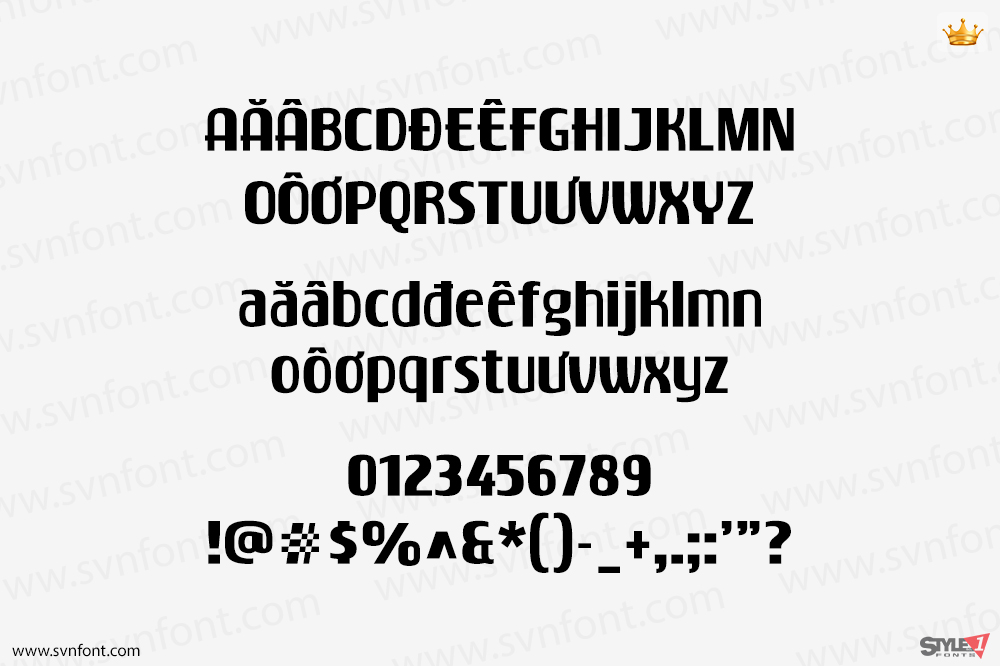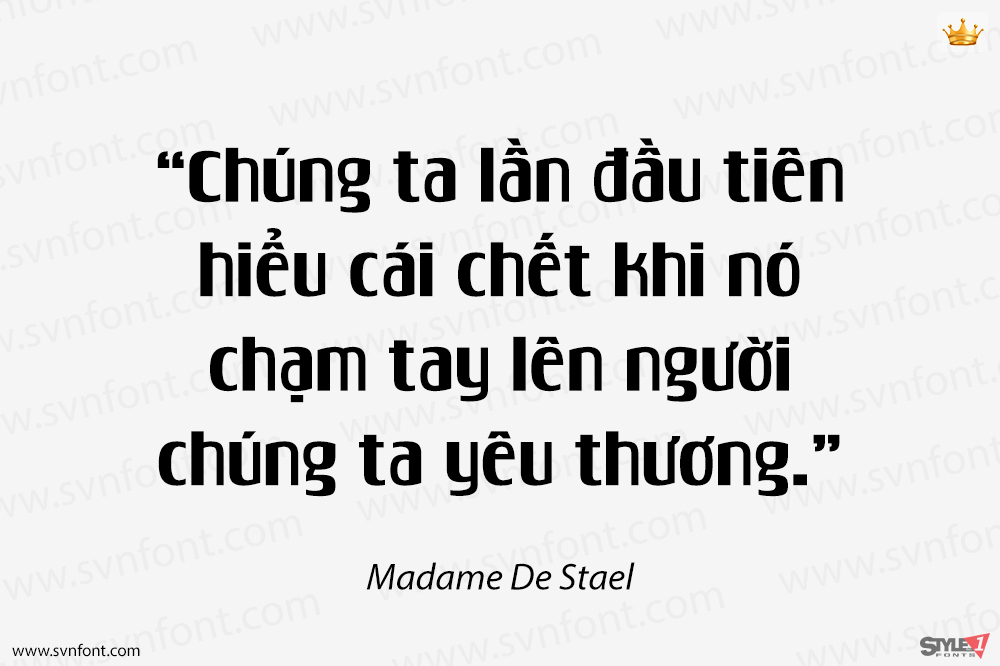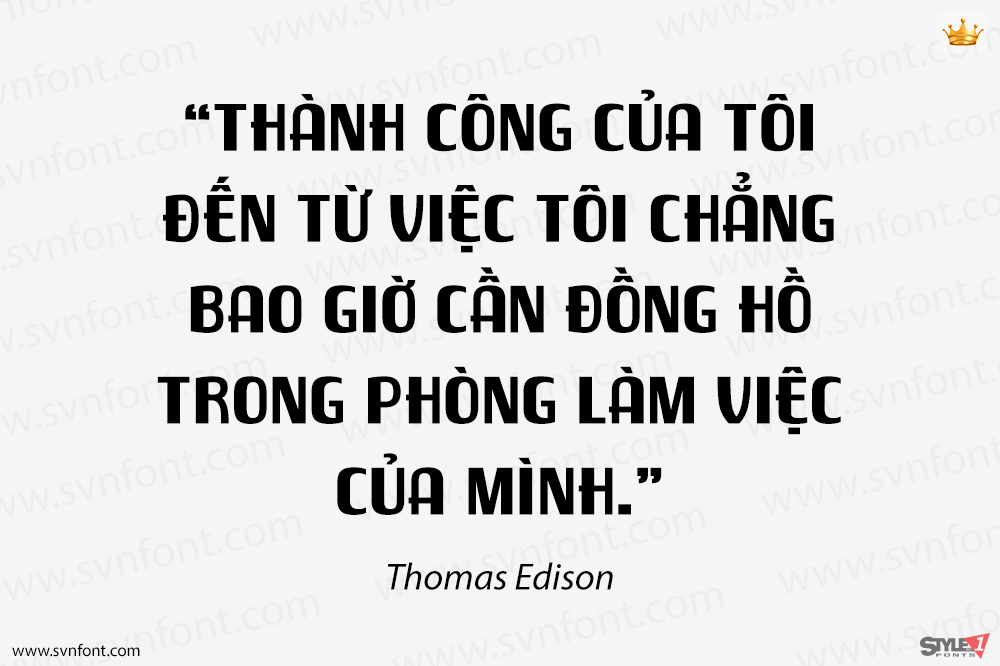
“CUMBANCHERA”, lấy cảm hứng từ nghệ thuật bìa album nhạc Latinh cổ điển. Cumbanchera gợi nhớ đến chủ đề âm nhạc mang tính biểu tượng, cổ điển và được công nhận «El Cumbanchero» do Rafael Hernández Marín «El Jibarito» sáng tác. CUMBANCHERA có thể được sử dụng chủ yếu trong tiêu đề, hiển thị và các đoạn văn ngắn. Hỗ trợ các ngôn ngữ Đông Âu. Bao gồm các chữ ghép tiêu chuẩn và tùy chọn, kiểu chữ thay thế cho chữ hoa và chữ thường, phân số, tử số và mẫu số, cùng các tính năng OpenType khác.
Nhà thiết kế: John Vargas Beltrán